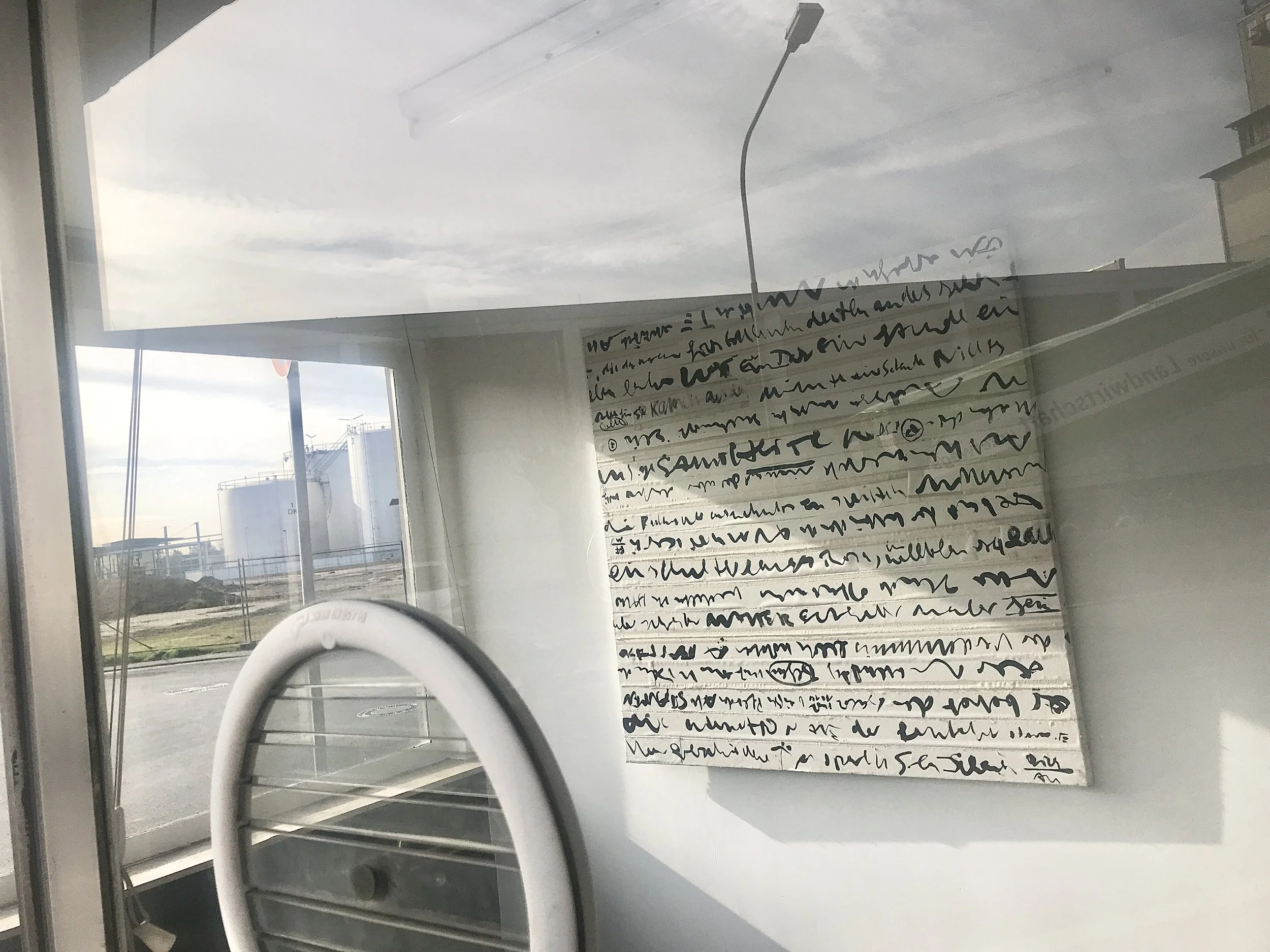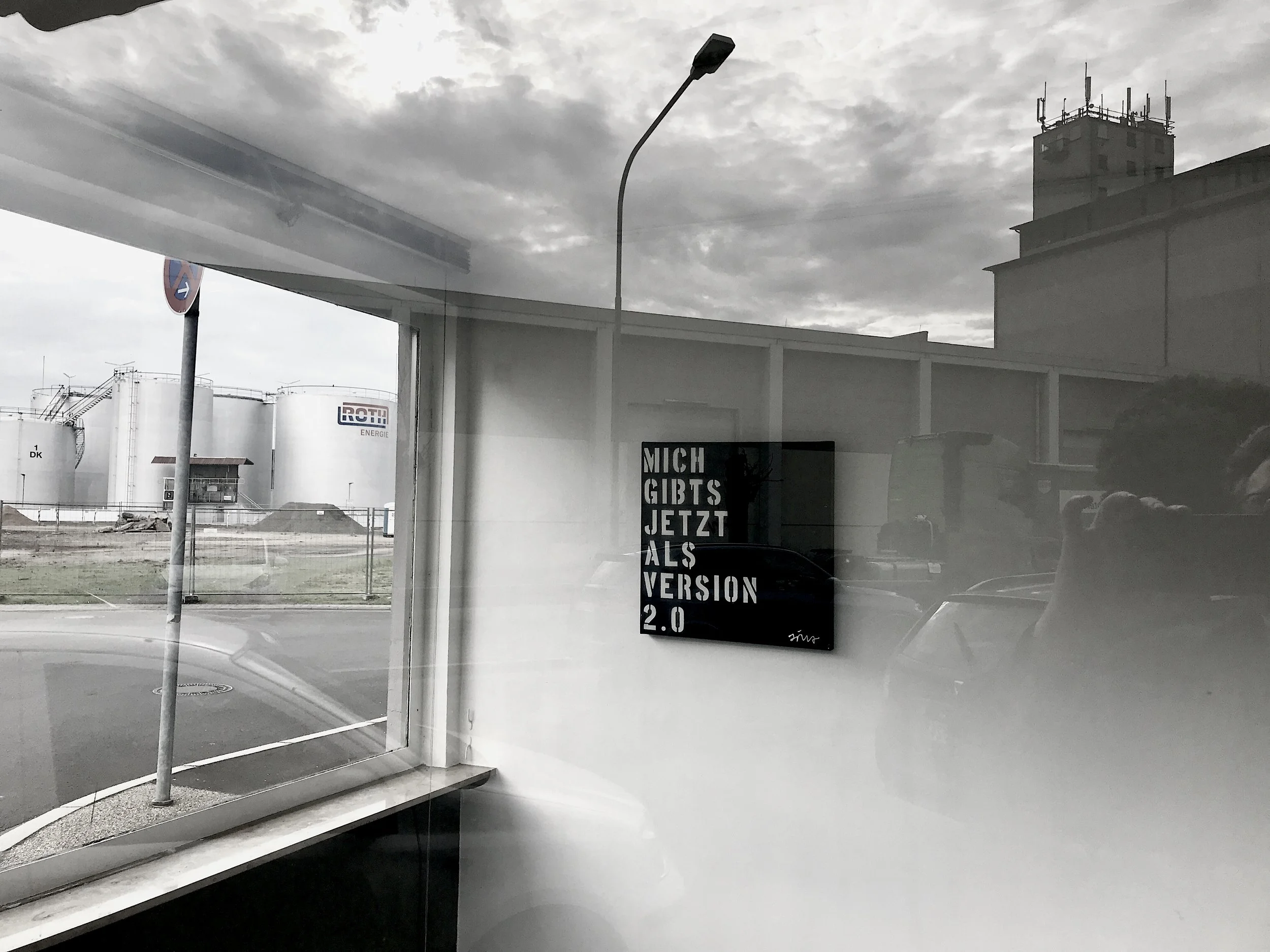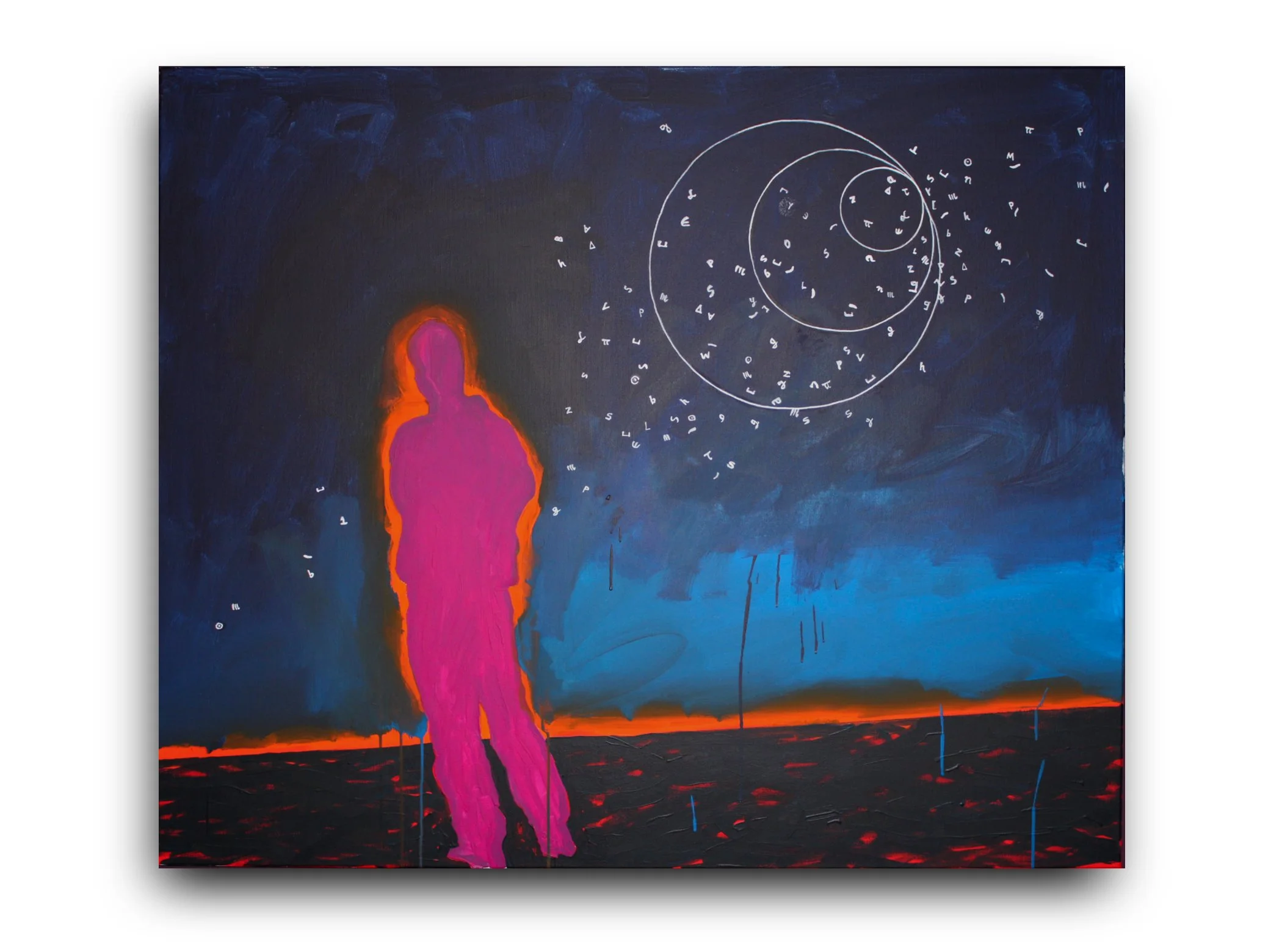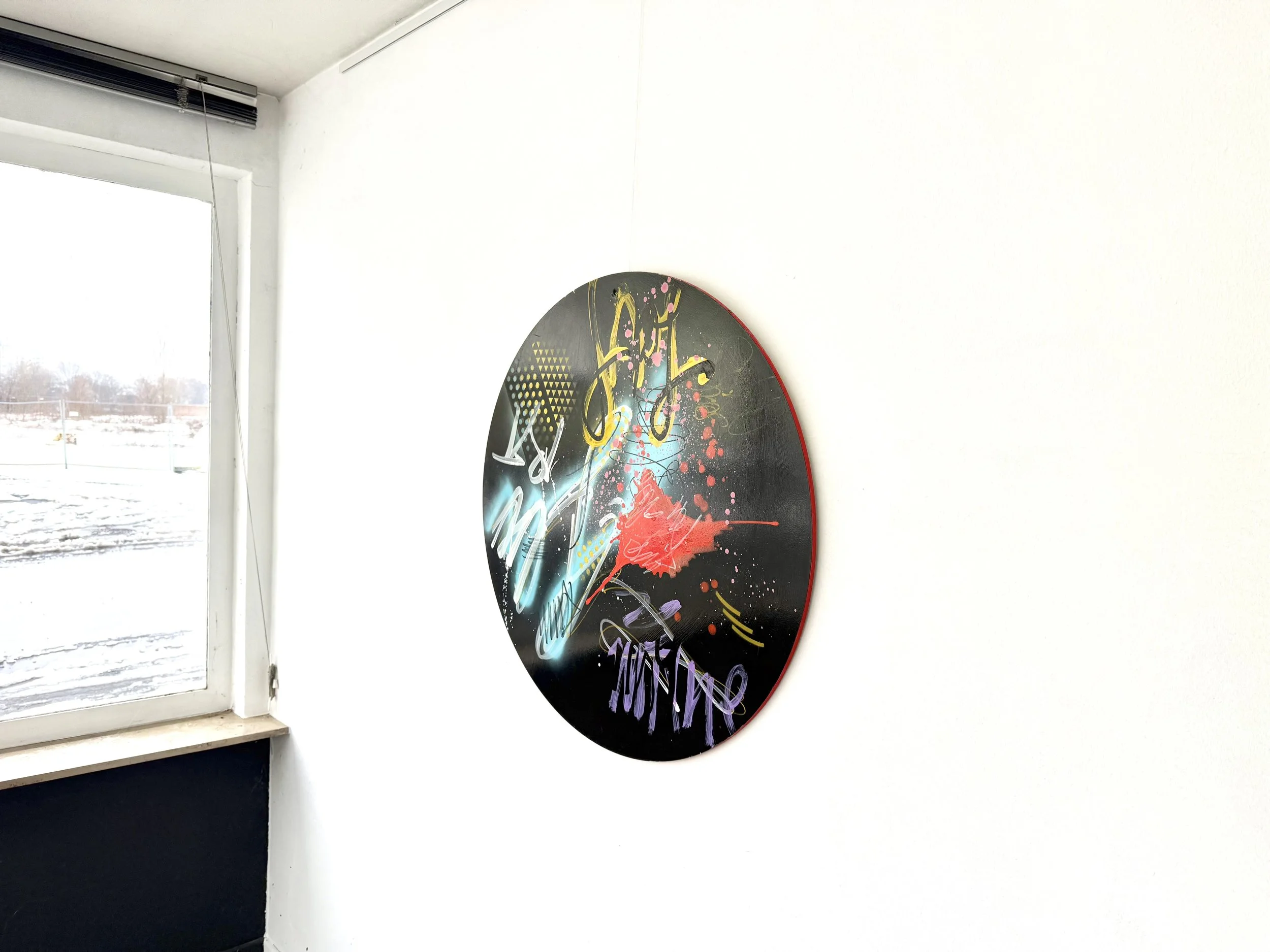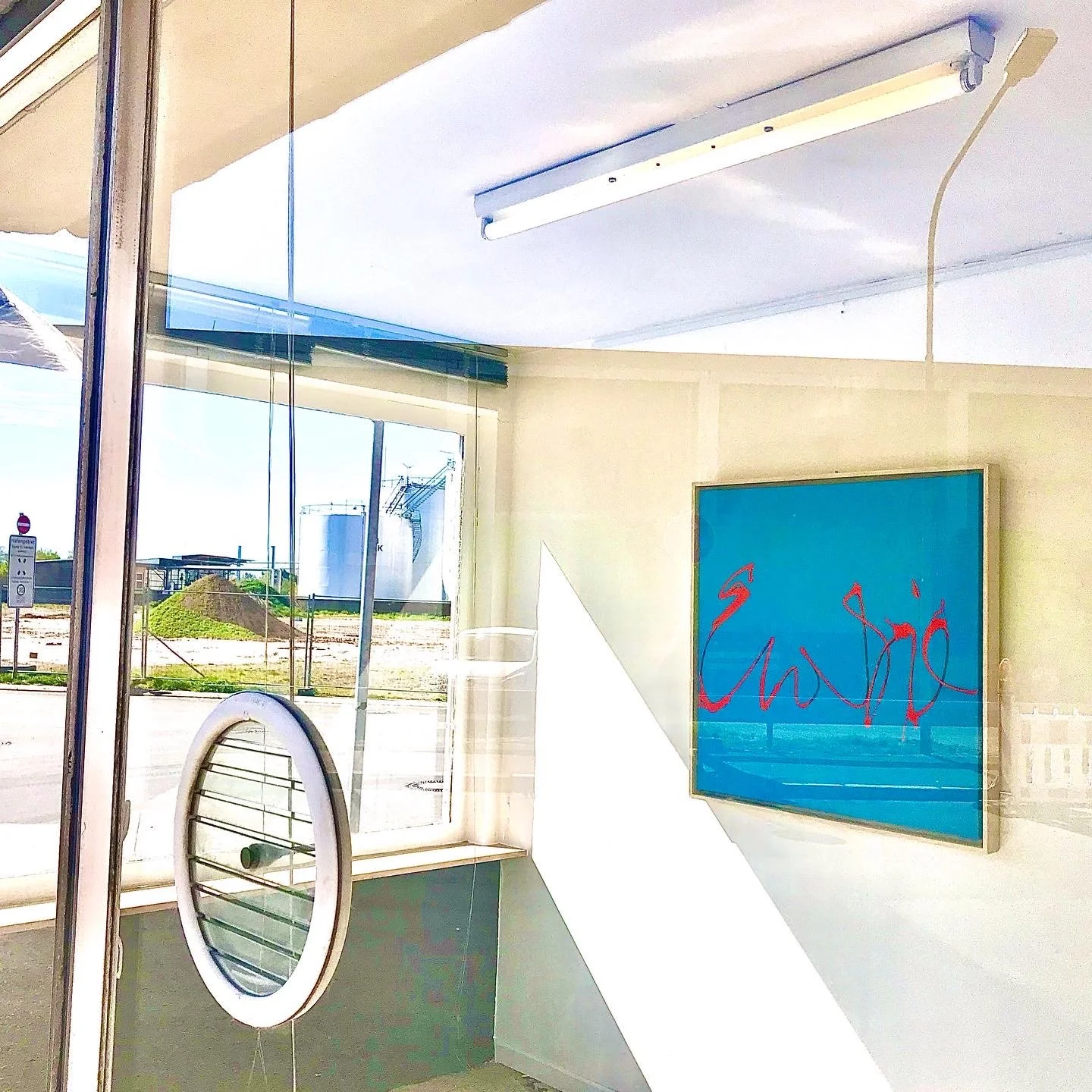
GALERIE SCHRIFT UND BILD
Schaufenster altes Hafenamt Hanau
Die 1-Raum-Galerie Schrift und Bild ist die wohl kleinste in Hanau, wenn nicht gar im Rhein-Main-Gebiet. In ihrem Schaufenster im alten Hafenamt Hanau in unmittelbarer Nähe zum Hafenbecken stellt sie immer wieder eine andere Arbeit oder eine Werkgruppe vor. Diese können von aussen betrachtet werden, wann immer die Jalousien oben sind…
Der Fokus der Arbeiten liegt stets auf dem Sammlungsschwerpunkt der Stiftung Schrift und Bild. Der Raum ist das ehemalige Wiegehaus des früheren Hafenamtes Hanau.
Schaufenster ehemaliges Wiegehaus
Im Schaufenster: Jörg Schmitz
Die zur Zeit ausgestellte Arbeit von Jörg Schmitz ist 2024 entstanden. In Mischtechnik auf Leinwand (120 x 100 cm) bringt Schmitz landschaftliche Assoziationen mit gestisch-skripturalen Elementen zusammen. Lichtreflektionen kommen in Form von silberfarbenem Schlagmetall ins Bild.
Es erscheinen Reflektionen von Momentaufnahmen möglicherweise vergangener Erinnerungen neben frischen und spontanen Spuren des Lebendigen.
Jörg Schmitz: Mischtechnik auf Leinwand, 120 x 100 cm
Im Schaufenster: Jörg Schmitz
In seiner frühen Arbeit »Splash« (2017, Mischtechnik auf Holz) beschäftigt sich Jörg Schmitz mit Mustern der Graffitikultur. Vom »tag« zum »template« streift er die Bildsprache(n) der street art und arrangiert sie zum klassischen Tafelbild.
Die runde Form erhöht die Achtsamkeit des Betrachters für die Komposition, die sich angst- und vorurteilsfrei vor den dekorativen Aspekten von Schrift, Geste und Form zeigt .
Im Schaufenster: Jörg Schmitz
Jörg Schmitz’ Arbeit »Himmlisches Alphabet« (2023, Acryl auf Leinwand, 100 x 120 cm) ist seine Hommage an die Buchstaben. Stand bislang die einzelne Geste im Mittelpunkt von Schmitz’ Arbeit, so widmet sich der Künstler seit 2020 verstärkt einer erzählenden Malerei wie in diesem Motiv.
Sprache – als Schrift, Buchstaben, Texte oder Fragmente – sind stets Teil von Schmitz’ Arbeiten. Dabei geht es weniger um eine Lesbarkeit im herkömmlichen Sinne sondern vielmehr um die Sprache als Material, das mit uns und mit unserem Alltag untrennbar verknüpft ist – als Gedanken-, Phantasien- und Geschichtenwelt.
Jörg Schmitz: »Himmlisches Alphabet« (2023)
Im Schaufenster 10. Oktober 2023–10.Januar 2024
Biarna Diegmüller ist die zweite Stipendiatin der Stiftung Schrift und Bild, die im Rahmen des Deutschlandstipendiums an der Hochschule für Gestaltung (HfG) Offenbach gefördert wird. Ihre Installation zeigt drei Textilobjekte mit bildhafter Typographie.
Im Schaufenster ab 28. März 2023
Über die Grenzen von Lesbarkeit hinaus geht das Werk von Künstler Jörg Schmitz. In seiner Arbeit ohne Titel aus 2010 (Tusche und Leinwandstreifen auf Leinwand, 140 x 140 cm) nutzt er eine über Jahre hinweg eigens entwickelte Schnellschreibmethode, mit der er Text zur Textur entwickelt. Buchstaben werden zum Muster und zum Ornament, die das Format flächig ausfüllt. – Das Bild ist käuflich zu erwerben. Kontakt hier
Im Schaufenster ab 10. November 2022
»MICH GIBTS JETZT ALS VERSION 2.0«, Acryl und Lack auf Leinwand (2008) von Jörg Schmitz greift ironisch den andauernden Erneuerungsdruck auf, der sich aus digitalen Welten auf uns alle übertragen hat. Die »Version 2.0« als ursprüngliche Bezeichnung für ein Software-Update hat es längst in unseren allgemeinen Sprachgebrauch geschafft. Zu diesem High-Tech-Begriff kreiert Schmitz’ Arbeit aus 2008 einen Kontrast durch die ausgeprägt sichtbare Handarbeit, mit der das Bild hergestellt ist. Die Signatur des Künstlers individualisiert den leicht absurd anmutenden Satz und steigert vielleicht sogar das Unbehagen darüber, dass wir uns alle allzuoft als bloße Konsumenten digitaler Geschäftsmodelle fühlen. – Das Bild ist käuflich zu erwerben; Nachricht bitte an mail@joerg-schmitz.com
Im Schaufenster 17. bis 21. Oktober 2022: Franz Weid
Als erster Stipendiat der Stiftung Schrift und Bild im Rahmen des Deutschlandstipendiums präsentiert Franz Weid seine typographische Installation »DIMENSIONAL FONTS« im Alten Hafenamt Hanau. Grosszügige Beiträge privater Förderinnen und Förderer haben erstmalig die Vergabe des Deutschlandstipendiums durch die Stiftung Schrift und Bild an der Hochschule für Gestaltung (HfG) Offenbach am Main möglich gemacht. Damit konnte auch die HfG in ihrem Ziel unterstützt werden, erstmalig ganze 50 Stipendien zu vergeben – ein bisheriger Rekord!
Auch in 2022/23 übernimmt die Stiftung Schrift und Bild wieder ein Deutschlandstipendium.
Im Schaufenster Mai bis Oktober 2022: Jörg Schmitz
Zum Bild
Die Leinwand (1 x 1 Meter, 2010, Acryl) zeigt ein in einem einzigen Zuge in wenigen Sekunden »geschriebenes« Wort. So wird die kraftvolle Entladung des Moments festgehalten. Die Information des Geschriebenen schwindet zugunsten seines kraftvoll-ungebremsten Ausdrucks.
In der arabischen Welt fungiert Schrift seit Urzeiten als Ornament in der Architektur oder als dekoratives Moment auf alltäglichen Gegenständen wie zum Beispiel Vasen oder Tellern. Auch hier geht Schrift oftmals weit über die Bedeutung des Wortes hinaus.
Zum Künstler
Jörg Schmitz (*1969 in Hannover), Studium an der Hochschule für Gestaltung (HfG) Offenbach am Main u.a. bei Prof. Friedrich Friedl, Prof. Ruedi Baur und Franz Mon (1926-2022).